字体视界于2014年成立,自有三大字库品牌,分别是义启字库、XFont和印品字库。
『义启字库』是非常受欢迎的手机主题商店字库品牌, 中文字库类型丰富多样, 多为个性应景类字库, 适合年轻化设计方案。
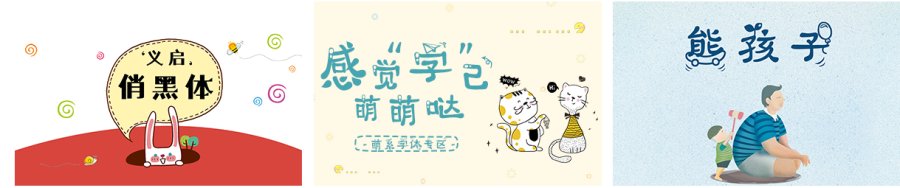
『XFont』字库品牌前身为“X手迹”,主打手写字体,手迹来自于不同年龄段的作者,从小孩到老人,每一款字都倾注了作者的心血,也带着作者自己的字体故事。
『印品字库』是中国专业的字库设计品牌,致力于打造高品质印刷、创意字体字库。每款字库均由设计师经过长时间的打磨而成,具有故事感及文化底蕴,风格特点明显。